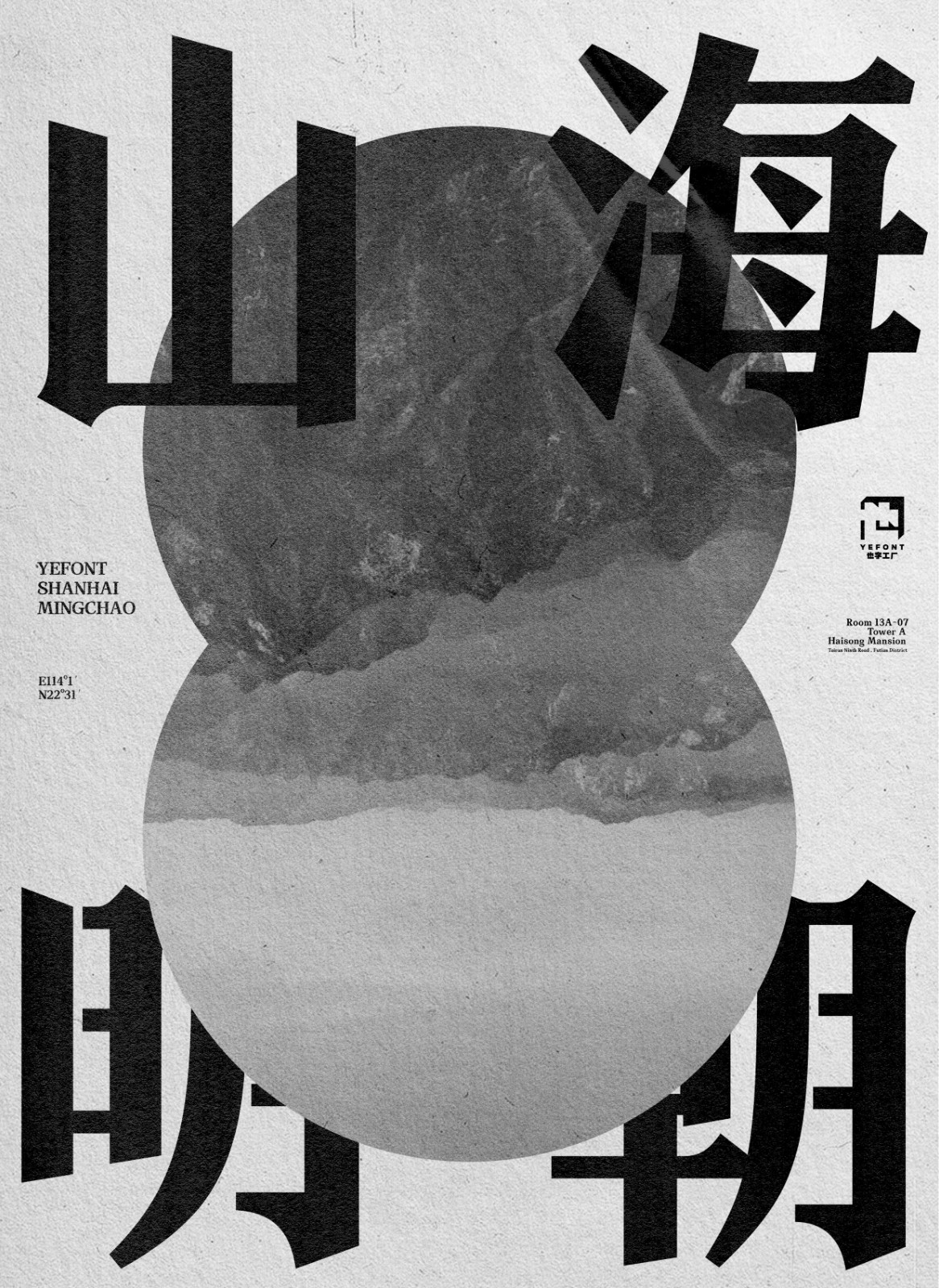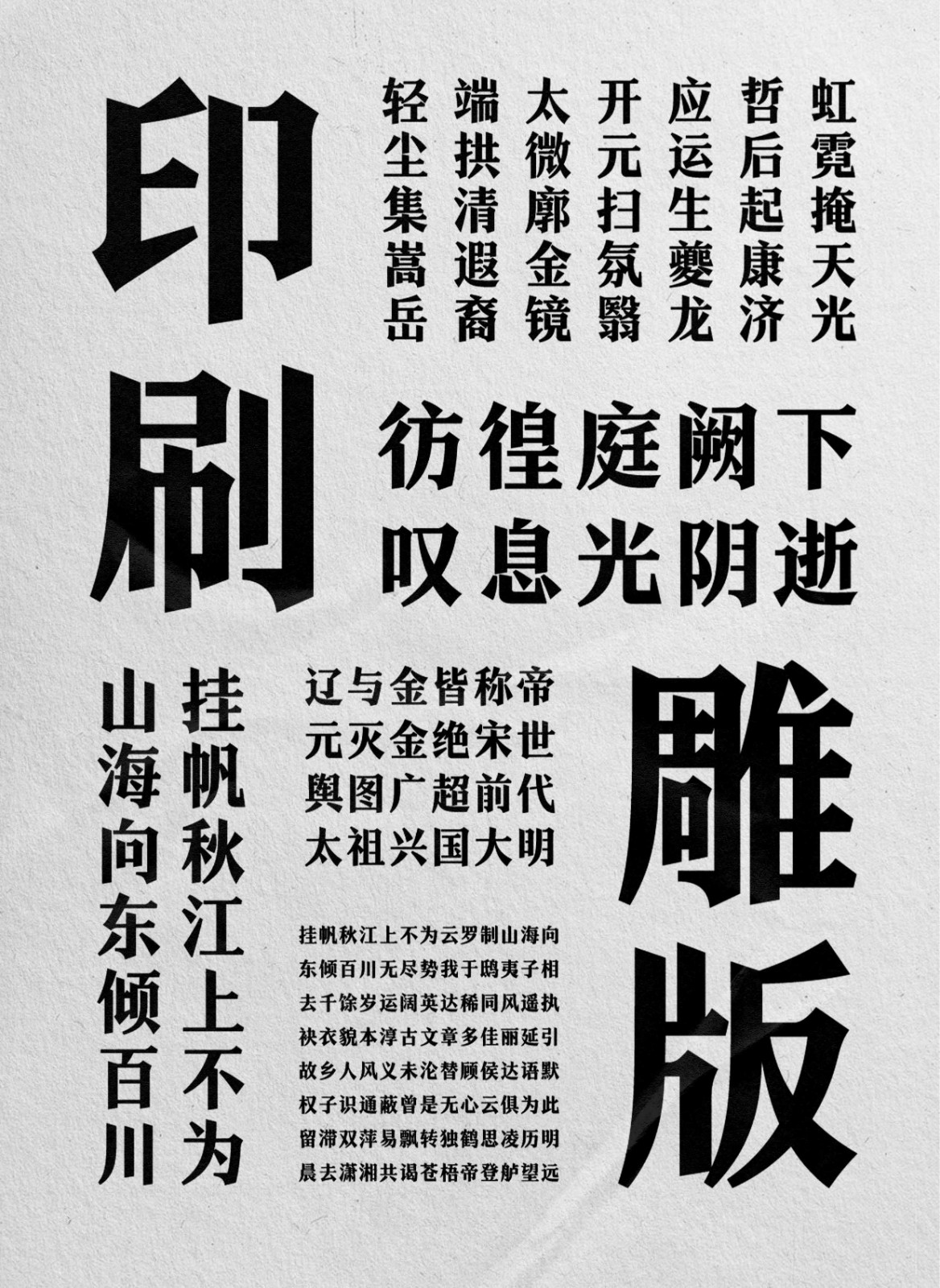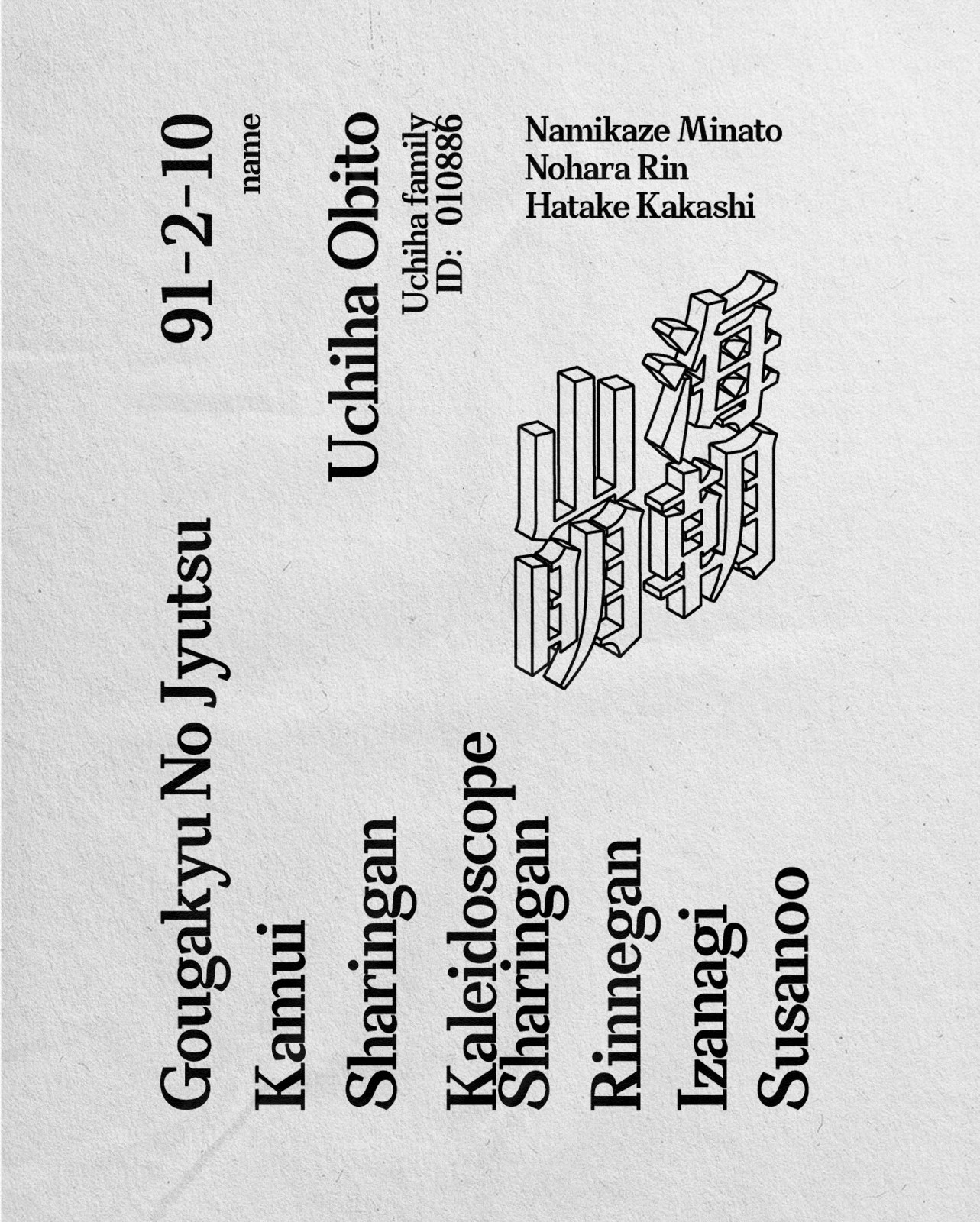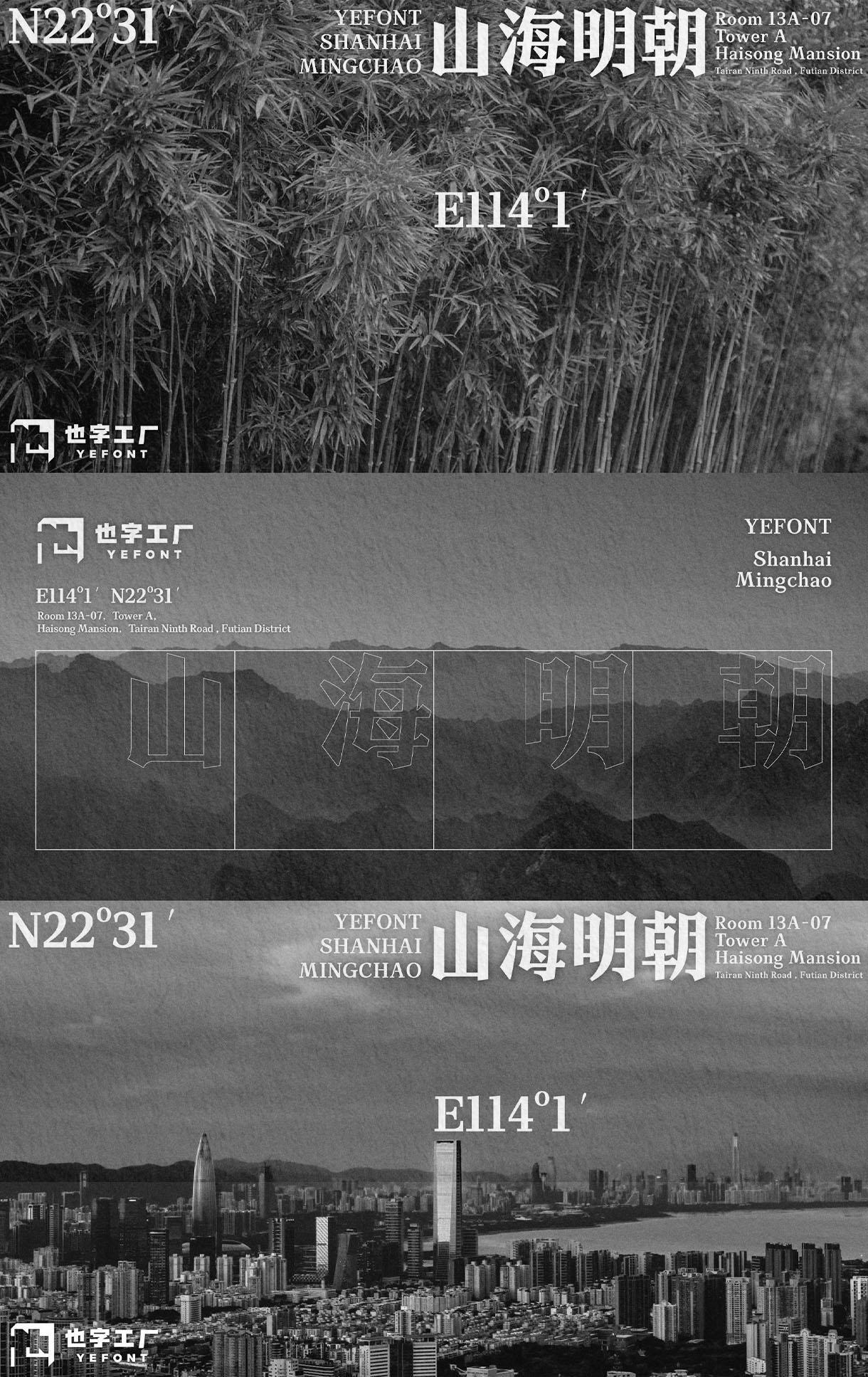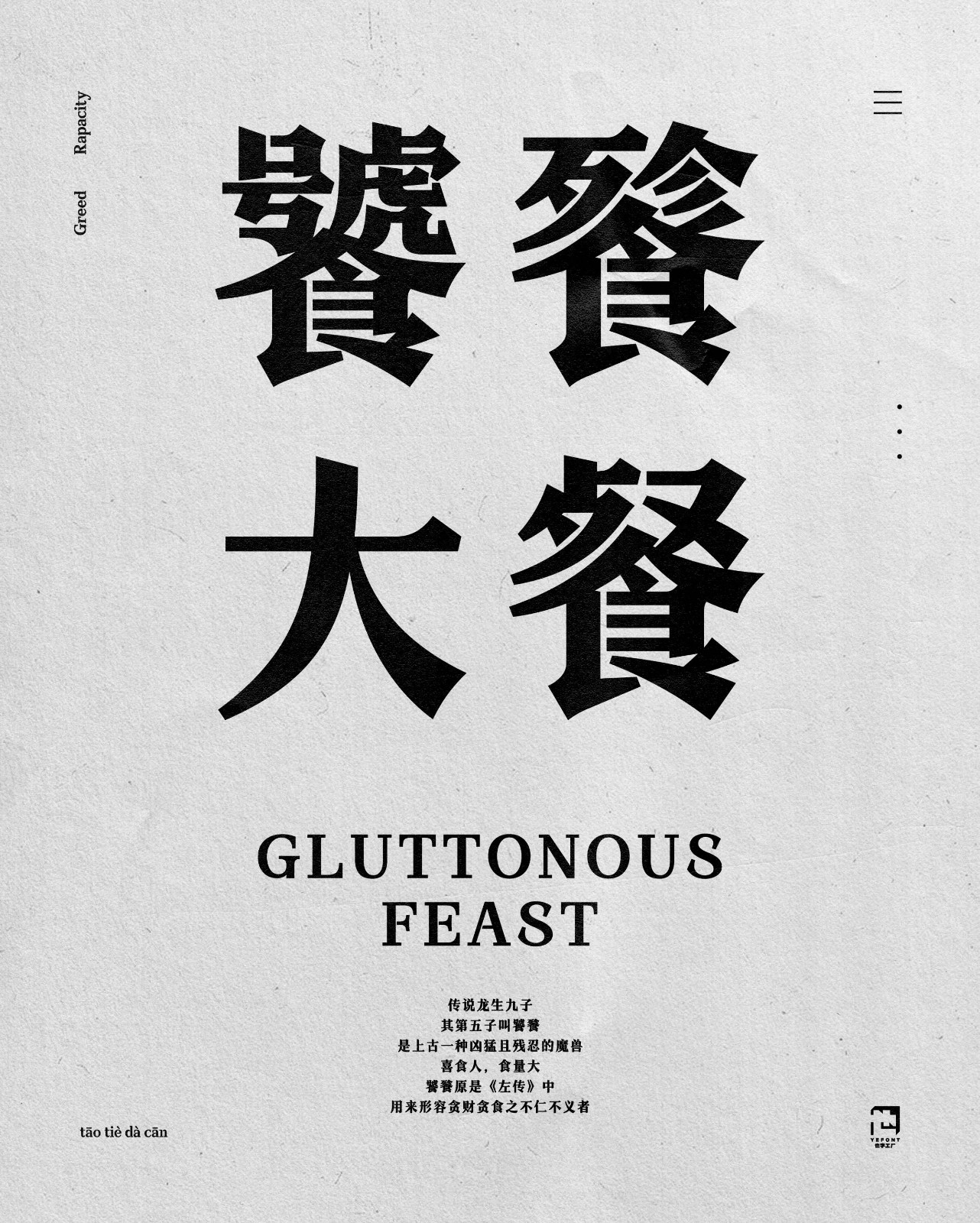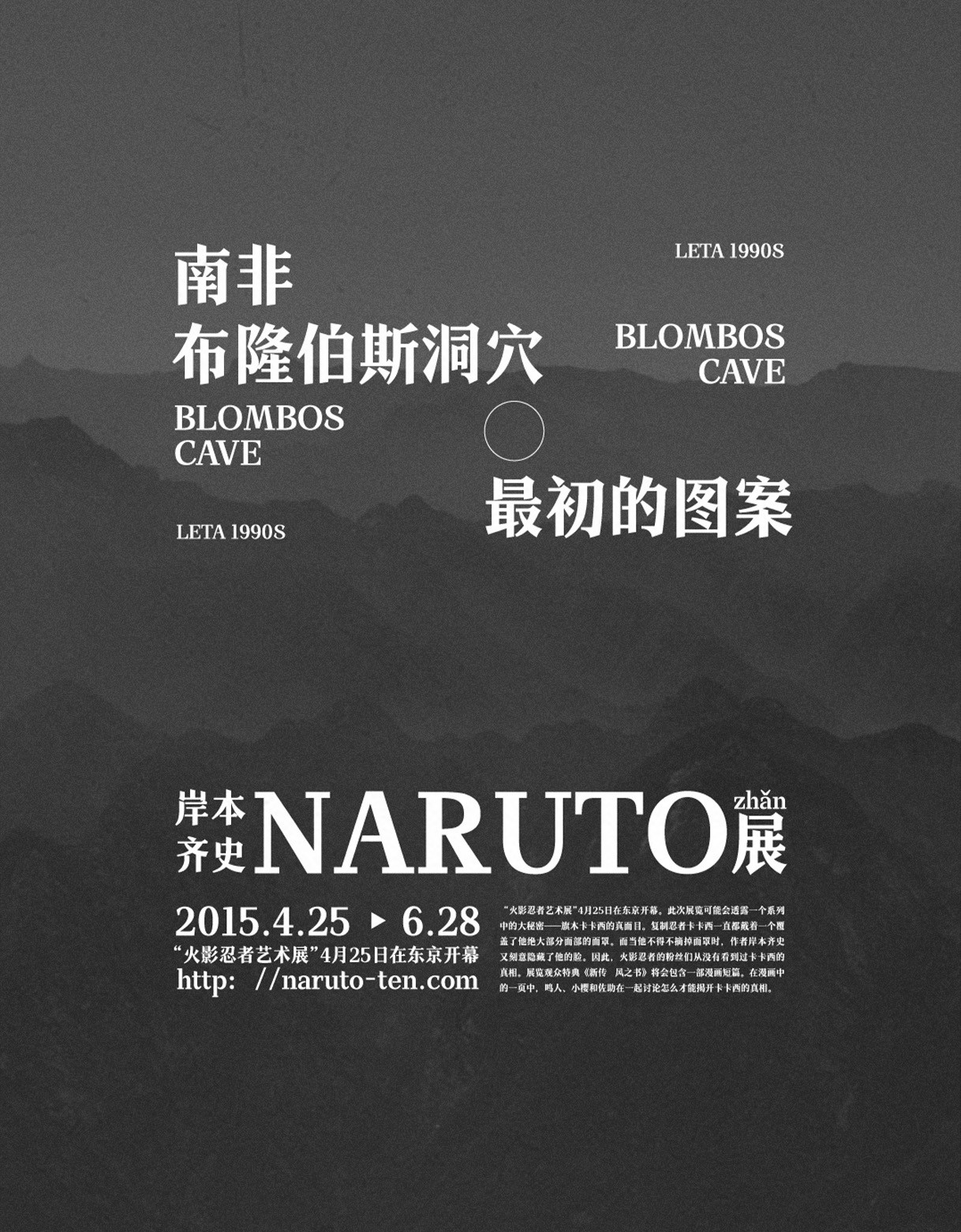
也字工厂|山海明朝体——介乎黑体与宋体的诗意
◉也字工厂山海明朝体是【也字工厂】专业字体设计师团队耗时一年打造的专业字;
山海明朝体的核心创意在于从“竹子”处汲取的断笔效果。“山海明朝”家族字规划了三种可选择的断笔样式,这让字体的气质更通透、更美观。同时让平面设计师能更多元、更自由的进行版面创作。
The core creativity of Shanhai Ming Dynasty style lies in the effect of broken strokes drawn from "bamboo". The family character "Shan Hai Ming Dynasty" has three optional styles of broken strokes, then the character is more transparent and beautiful. At the same time, it is free for graphic designers to create layouts with more variety and freedom.
这也是也字工厂推出的第一款精品字体,耗时半年打造。以山为界,描绘山河:以海为媒,拨弄潮汐;以竹承载,传承历史。取“山海明朝”也是在鞭策自己,胸怀山海,虚怀若谷,真诚造字,精益求精,打造跨越时代存在的字体。
This is the first boutique font launched by Yezi Club, which took half a year to create. Taking mountains as boundaries to depict mountains and rivers: using the sea as a medium to fiddle with the tides; using bamboo as a carrier to inherit history. Taking the "Shan Hai Ming Dynasty" is also a spur to oneself, with the mountains and seas in mind, with an open mind, creating characters with sincerity, striving for perfection, and creating a font that exists across the times.
宋体字迹清晰、疏密适当,黑体横平竖直、抢眼醒目。宋体和黑体是两种不同的结构和美学系统,前者具有古色古香的视觉效果,长时间阅读不易疲劳,适合做正文排版;后者字型端正,严肃但稍欠美感,字号小的黑体清晰度较差,因此更适合用于文章标题排版。
The Song font is clear in handwriting and appropriate in density, while the boldface is horizontal and vertical, which is eye-catching. Song font and Boldface are two different structures and aesthetic systems. The Song font has an antique visual effect and it is not easy to be tired after a long time, so it is suitable for text typesetting. The Boldface is upright font, serious but slightly less aesthetic. Which is small size of the black font and less clear. So it is more suitable for article title typesetting.
结合两者优点,我们希望山海明朝体给人的视觉感观是大气的,端正且富有趣味性、醒目易读却不呆板。既能满足用于标题字,也能在正文排版中使用。
Combining the advantages of the two fonts, we hope the visual perception of Shanhai Ming Dynasty style is atmospheric, upright, interesting, eye-catching and easy to read but not rigid. It can not only be used for title words, but also can be used in text layout.
山海明朝体在黑体架构上加入了宋体的衬角装饰,并对衬角造型进行了大量优化,切掉点、撇、捺、钩等笔画的尖端,调整撇、捺的整体曲率和笔画长度,适当减少宋体柔美的书写特征,保留黑体硬朗的转折特点。在理性的框架中融入感性,协调两者之间的特征占比。
The Shanhai Ming Dynasty style has been added the lining corner decoration of Song font to the boldface, and has been made a lot of optimization on the lining angle shape, such as cutting off the tips of strokes such as dot, skimming, stroking, hook, etc… Adjusting the overall curvature and stroke length of skimming and stroking, reducing the soft and beautiful writing characteristics of the Song font appropriately. Retaining the tough turning characteristics of the boldface. Integrate sensibility into a rational framework and coordinate the proportion of features between the two.
在山海明朝体的创意阶段,我们倾向于关注字体的实际应用效果。从平面设计的艺术效果和实用效果来考虑,一是做标题需要醒目和美观,二是字体本质即传达信息的功能,识别度要高。
In the creative period of Shanhai Ming Dynasty style, we try to focus on the practical application effect of fonts. Considering the artistic effect and practical effect of graphic design, one is that the title needs to be eye-catching and beautiful, the other is the essence of the font which is the function of conveying information, whose recognition degree should be high.